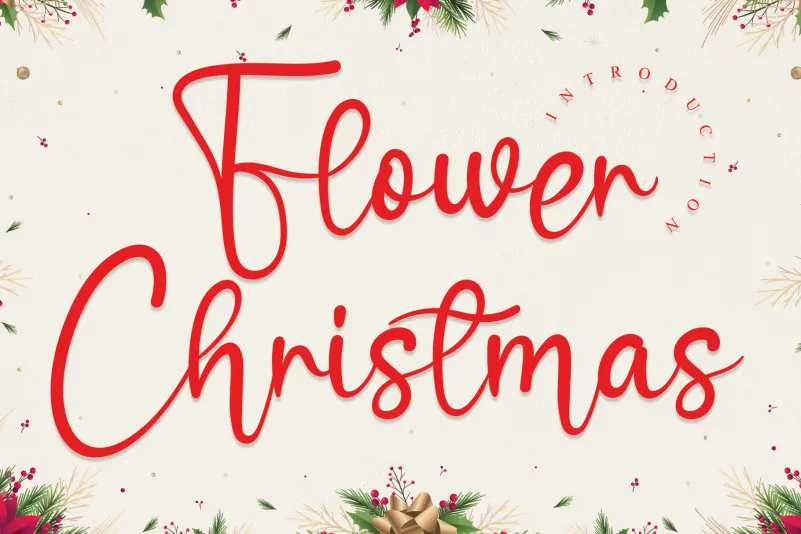
Aqui está uma descrição envolvente para a página de download da fonte ‘Flower Christmas Script Font’, seguindo as regras fornecidas: ‘Flower Christmas Script Font é uma linda mistura do estilo script que oferece um toque delicado e refinado às suas criações. Inspirada nos traços elegantes das fés de Natal, essa fonte tem uma natureza encantadora e festiva, perfeita para aqueles designers em busca de algo único e criativo para seus projetos gráficos. Com seus detalhes cuidadosamente trabalhados, essa font será sua escolha ideal para adicionar um toque especial a qualquer projeto que precise de um ar de delicadeza e romantismo. Criado pelo designer creativeletter, este script oferece um grande potencial tanto para designs de anúncios e publicidade quanto para ilustrações e mensagens digitais. Seja em uma carta de Natal personalizada ou uma mensagem emocionante no LinkedIn, o uso dessa fonte certamente fará sua marca brilhar ainda mais. Descubra a magia dos traços da Festa do Natal com ‘Flower Christmas Script Font’ – sua próxima adição à coleção de suas ferramentas digitais.’